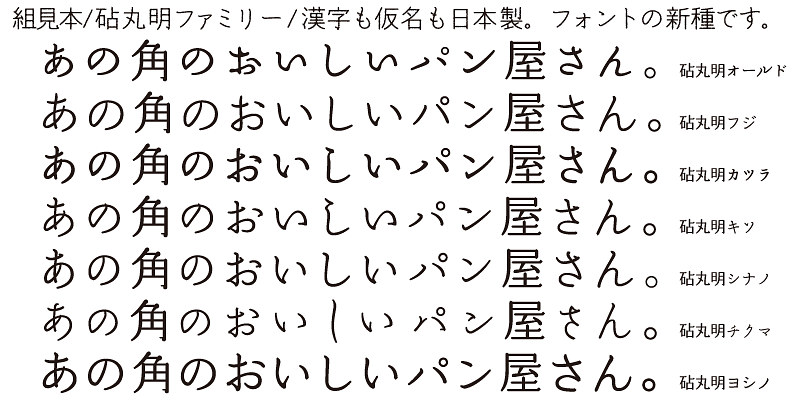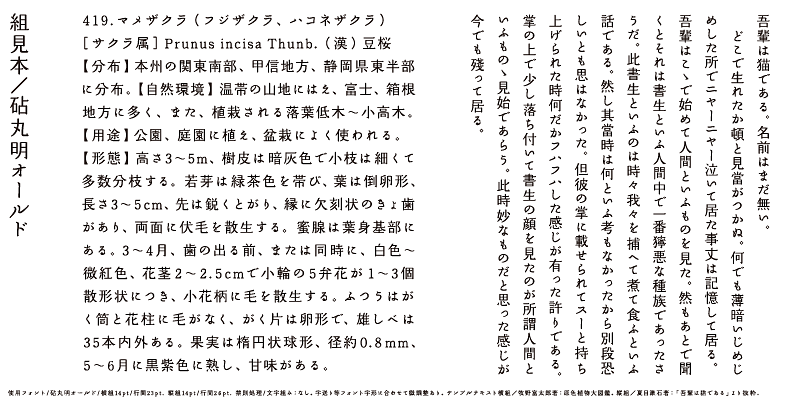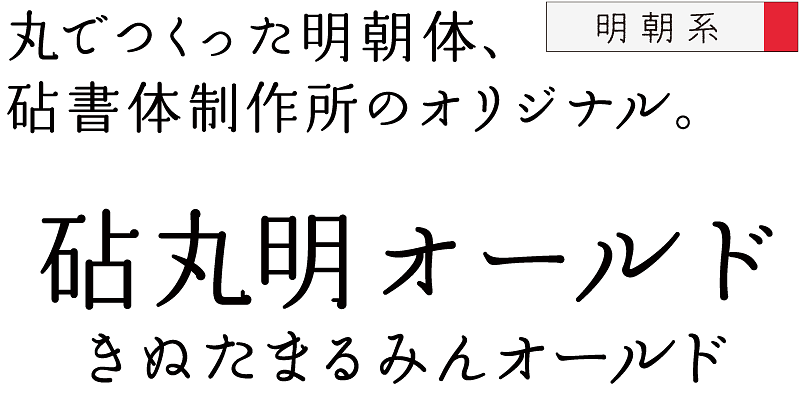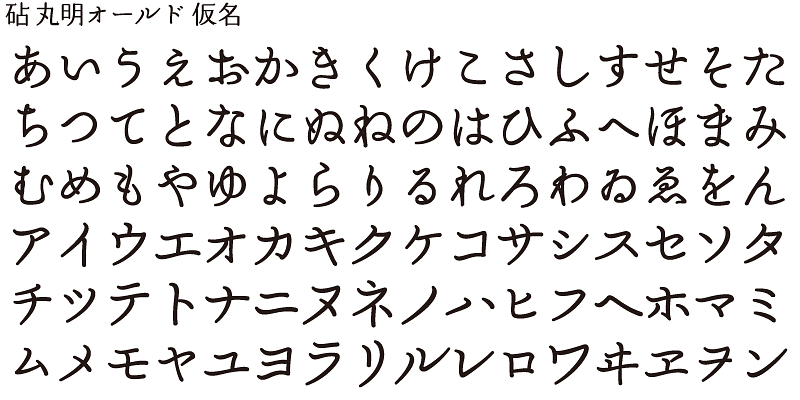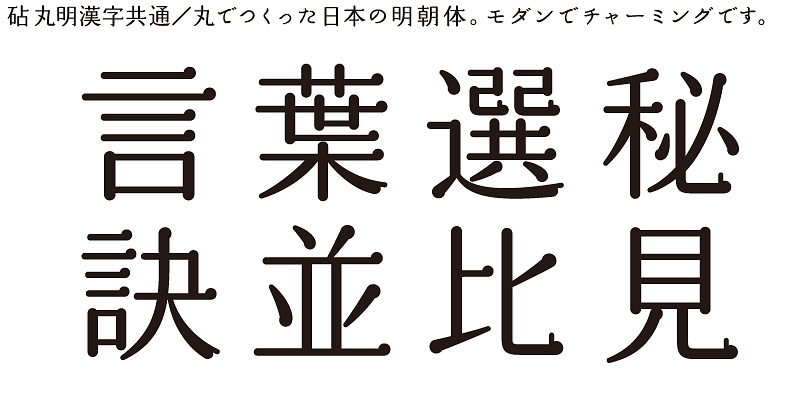
「丸明オールド」のかな文字は、懐かしくてモダンなデザイン。かな文字は漢字よりもかなり小さくなっていますが、縦に組んでも横に組んでもきれいに読みやすく収まります。
丸明は、すべてのバリエーションで漢字 (表意文字) のデザインが共通です。丸明の漢字のデザインは日本の明朝体の基本スタイルを継承しつつ、ストロークのエレメントに丸を使っているのが特徴です。縦線、横線、点、トメ、ハネ、ハライなどどれも先端が丸くなっています。丸明に合計 7 つのバリエーションがあり、「丸明朝体」に新風を吹き込みます。
日本語の特長は、仮名をつかいます。仮名は、中国か らやってきた漢文を日本語読みにするために、日本が 作った文字です。仮名は意味をもつ漢字を主役に言 葉をつないでいきます。それは日本人の優しさや気づ かい、ときにはあいまいさもありますが、どれも小さな 国の人の密度が高い暮らしから生まれた言葉です。 砧(きぬた)書体制作所は、仮名が日本語の原点だ と考えています。その仮名を豊かにすれば、日本語は もっと魅力的になります。日本語の60〜70%は、仮 名です。仮名をかえると文字組の表情もかわります。 仮名はシンプルで動きのある曲線構成、その表現は、 無限の世界です。日本語の豊かさは、仮名に託されて います。砧書体制作所のフォントに仮名のバリエー ションが多いのはそのためです。